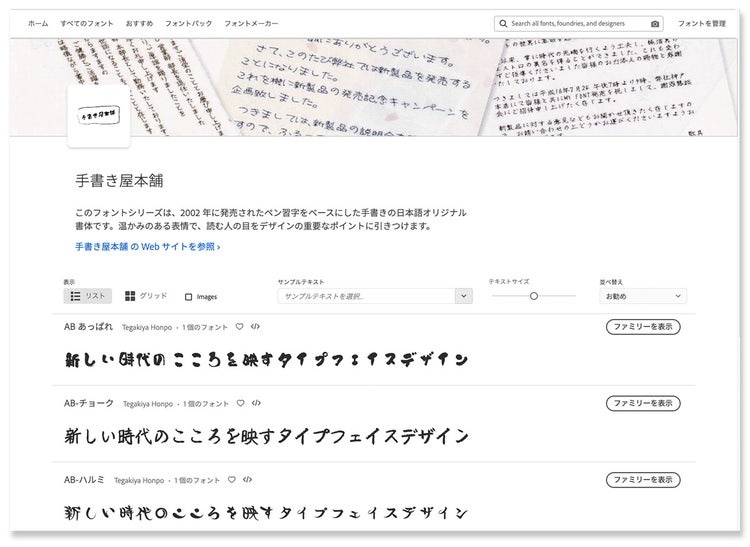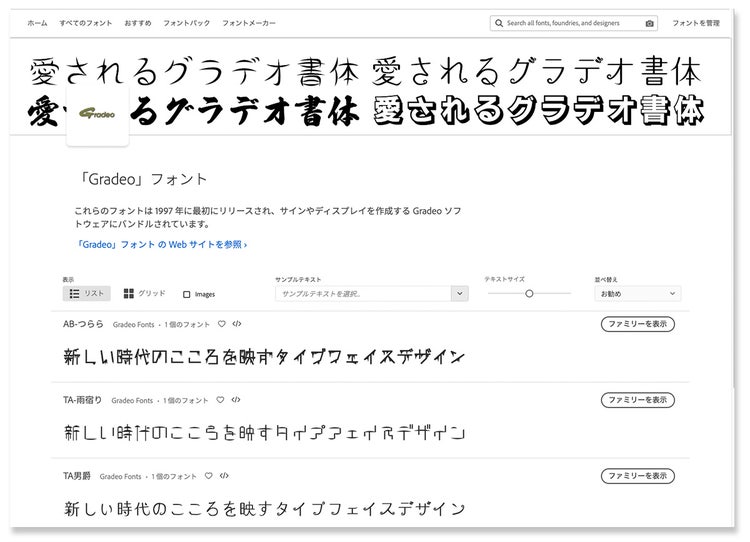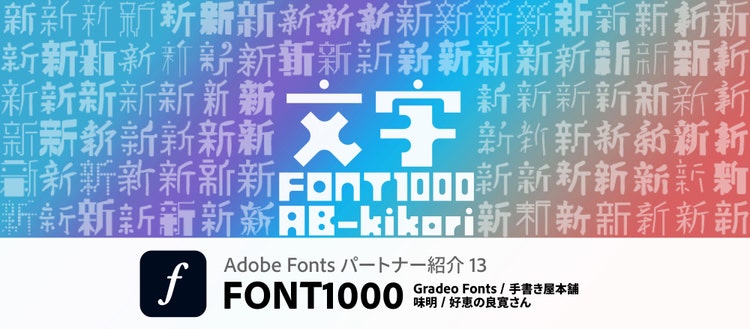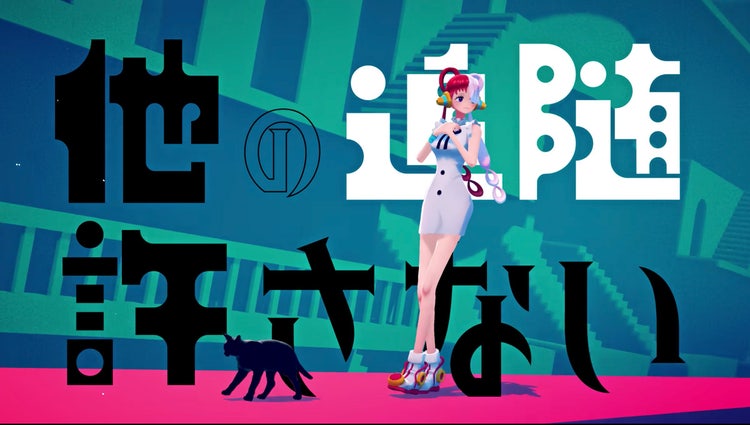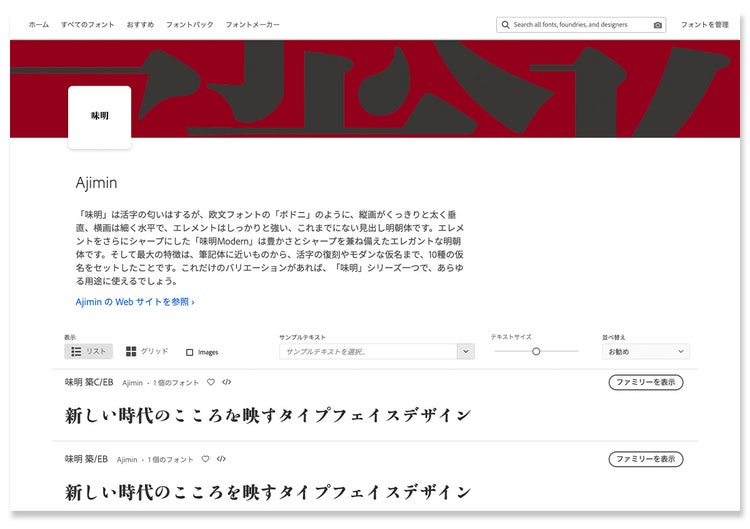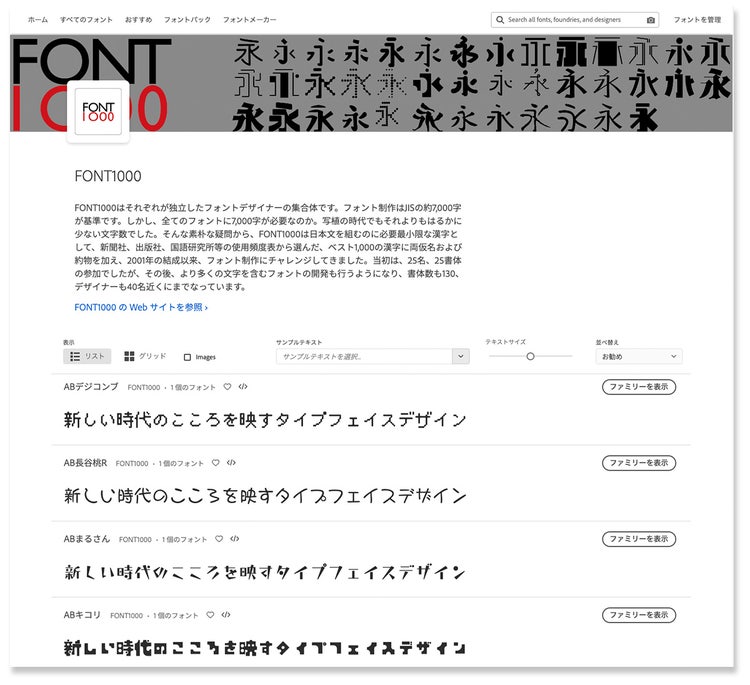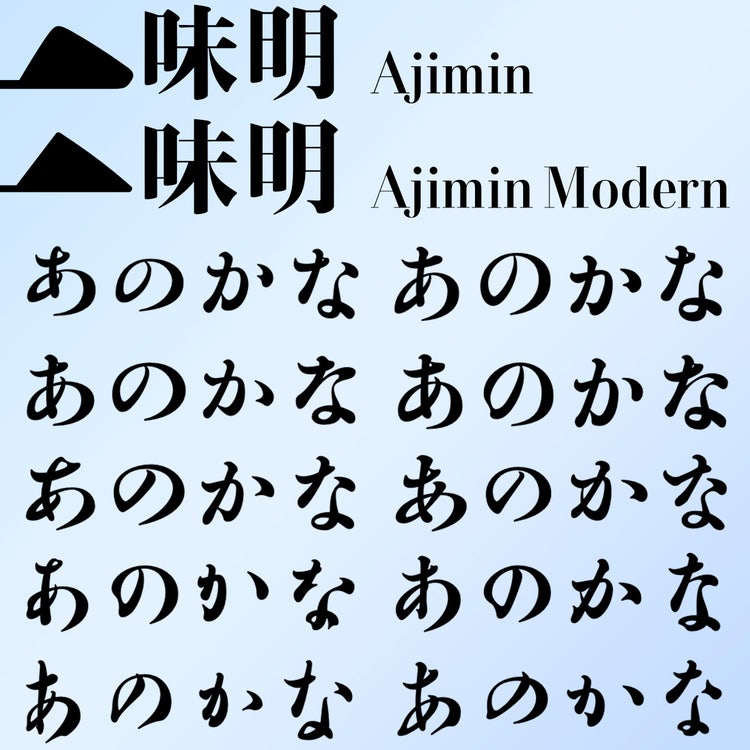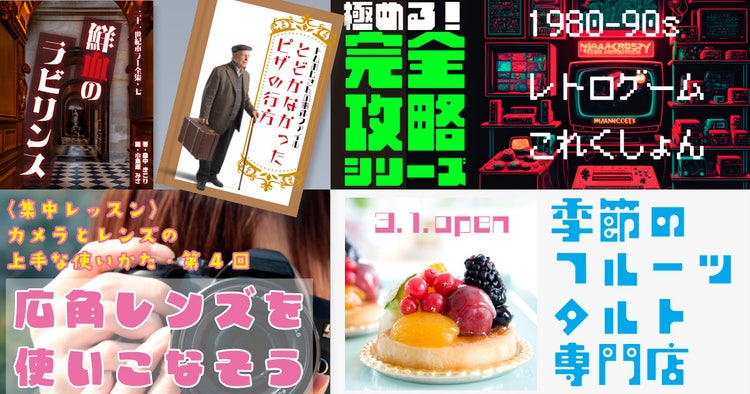
個性あふれるデザインフォントが集結した「FONT1000」 今回のフォントメーカー紹介では、FONT1000を中心に5つのブランドを取り上げます。FONT1000はタイプデザイナーを中心に結成されたプロジェクトで、日本語の文章を組むのに必要な最低限の漢字1,000字に、ひらがな、カタカナ英数字、句読点等の約物を加えた文字セットを作り、それまでの書体にはない造形、筆法にチャレンジする実験的な取り組みとしてスタートしました。このプロジェクトには、「築地」「良寛」「小町」「行成」「弘道軒」等を手がけた味岡伸太郎さん、「きりぎりす」「はるひ学園」で知られる七種泰史さん、モリサワの人気書体「すずむし」をデザインした豊島晶さん、ロゴデザイナーとしても有名な成澤正信さん等が参加。錚々たるメンバーから発表される斬新で目を惹きつけて止まない書体たちは、デザイナーの感性を大いに刺激することになりました。従来のフォントにはない個性的なデザインは、MV等で文字がモーショングラフィックとして扱われるようになった昨今、ふたたび注目を集めており、Adoさんが歌う「ウタカタララバイ」では、リリックを織りなすフォントのひとつとしてFONT1000の「キコリ」が採用されています。
【Ado】ウタカタララバイ(ウタ from ONE PIECE FILM RED)
FONT1000のフォントは、その後、テクノアドバンス社(当時/後述)の技術協力を受けて、漢字字種を拡張。それまで1,000字だった漢字は2,286字まで増え、合計約2,600字を収録したTA版(=TechnoAdvance)として販売を開始しました。Adobe Fontsでは、FONT1000の131書体のうち、94ファミリー・96書体がFONT1000ブランドで提供されています(一部のFONT1000書体は、スキルインフォメーションズにOEM提供されており、Adobe Fontsからも利用可能)。Adobe Fonts/スキルインフォメーションズ https://fonts.adobe.com/foundries/skill-information-s-co-ltd
FONT1000のフォントは、Adobe Fonts版(AB)と製品版(TA)で収録している文字数に違いがあります。フォント名に「AB-」がつくAdobe Fonts版は、漢字1,000字にひらがな、カタカナ、英数字、約物等を加えた1,206字に留まります。Adobe Fontsでデザインを試し、文字に不足を感じたら、フォント名に「TA-」がつく製品版フォントを導入するとよいでしょう。
フォント制作を支え続けるウェブフォントジャパン FONT1000がTA版としてリリースされ、現在、Adobe Fontsでも利用可能になった背景には、片岡正さんという立役者の存在がありました。片岡さんは1996年にテクノアドバンス社を設立し、サイン&ディスプレイ業界向けにカッティングマシンソフト「Gradeo」を発表。あわせて専用フォントを開発します。2001年には特定の漢字から別の漢字を自動生成する「フォントウィザード」、2002年には自分の手描き文字をフォントにする「マイフォント」、2003年には日本初となるWebFontサービス、手書きデザインフォントを専門に扱うブランド「手書き屋本舗」と次々にフォントサービスを手がけました。その後、FONT1000プロジェクトで代表を務めていたタイプデザイナーの味岡伸太郎さんと出会った片岡さんは、「フォントウィザード」の自動生成エンジンをカスタマイズすることで、FONT1000のフォントが持つ1,000字の漢字を2,286字まで拡張することに成功。これによってFONT1000のフォントは製品として販売できるようになったのです。
片岡さんは2022年6月、ウェブフォントジャパンを新たに設立。現在、Adobe FontsではFONT1000に加えて、Gradeoフォント、手書き屋本舗、味明(Ajimin)、好恵の良寛さん(Yoshie no Ryokan-san)、計5ブランドを展開しています。以降、FONT1000以外の4つのブランドについて、その特徴を紹介します。
カッティングマシン用に作られた「Gradeo フォント」 Gradeoフォントは、片岡さんがカッティングマシンソフト「Gradeo」向けに開発したフォントです。明朝、角ゴシック、丸ゴシックのほか、個性的なデザインフォントも揃い、Adobe Fontsでは13ファミリー・24書体が提供されています。
質の高い回文字フォントを提供する「手書き屋本舗」 手書き屋本舗は、より質の高い手書きフォントを提供するために片岡さんが2003年に立ち上げたフォントブランドです。ほどよいクセ字からチョークや筆の質感を生かしたものまで表現の幅広さが特徴で、Adobe Fontsでは18書体が提供されています。
味岡伸太郎さんが手がける見出し用明朝体「味明」 味明(Ajimin)は、タイプデザイナー・味岡伸太郎さんによる見出し明朝体「味明」を提供するブランドです。2種類の漢字(味明)と10種のかな(味かな)によって構成され、その組み合わせによって多様なバリエーションを実現しています。漢字のウェイトはEBのみですが、10種のかなはそれぞれ10のウェイト、合計10×10=100書体を揃え、EB以外の味かなを使う場合は、各ウェイトに合わせて既存のフォントと組み合わせて使用します。書風の変化に加え、ウェイトがしっかり揃っているため、明朝体の表現力をこれまで以上に高めることができるでしょう。Adobe Fontsではこのうち、味明・味明モダンの2種類の漢字に、それぞれ10種の味かなを組み合わせた・20書体が提供されています。漢字:味明+かな:築・築C・秀・秀L・秀V・民・行・弘・良・草(計10書体)漢字:味明モダン+かな:築・築C・秀・秀L・秀V・民・行・弘・良・草 (計10書体)
良寛の臨書を書体化した「好恵の良寛さん」 好恵の良寛さんは、江戸後期の禅僧・良寛の墨跡をもとに作られた書体をリリースしているフォントブランドです。フォント名はブランド名と同じ「好恵の良寛さん」で、筆で臨書した文字をもとに作られた「好恵の良寛さん」とサインペンで臨書した文字をもとにした「好恵の良寛さん Pen」の2種類が各3ウェイト提供されています。Adobe Fontsではこのうち、筆文字タイプの「好恵の良寛さん」3書体を利用することができます。
SNS・映像でもインパクト大!個性際立つフォントパック Adobe Fontsで使用可能な多くのフォントのなかから、イメージや目的にあわせて厳選して提供する「フォントパック」に、「インパクト抜群!個性際立つフォントパック」が追加されました。FONT1000・96ファミリーのなかから、しっかりとした太みがあり、個性の強いフォントを10点セレクト。グラフィックデザインだけでなく、webバナーやSNS、映像でもそれまでのフォントにはない、インパクトのあるデザインに仕上げることができます。
ABキコリ
ABまるさん
ABキリギリス
ABカントリーロード
ABドラミン
ABクワドラ
ABJグー
AB探偵団
AB Tori A
AB Megadot9